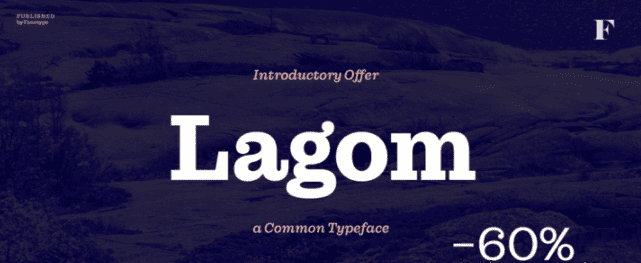
Вы находите некоторые современные шрифты слишком холодными, сдержанными и даже высокомерными?
Вот чем можно очаровать ваших обеспокоенных клиентов - Lagom, семейство вежливых и дипломатических шрифтов.
Используйте Lagom, и вы сможете достичь той самой тонкой грани между изысканностью и обыденностью.
Шрифт отлично подходит для товаров повседневного спроса (FMCG, fast moving consumergoods), фирменных стилей ресторанов, меню или систем поиска пути - вы даже можете попробовать его в мобильном приложении, чтобы почувствовать себя более человечным и простым в обращении.
Шрифты Lagom, идеально подходящие для современных нужд, оснащены интеллектуальными функциями Open Type, а семейство шрифтов имеет оптимальный размер - не слишком большой и не слишком маленький.
Сделайте свою жизнь дизайнера проще с Lagom!